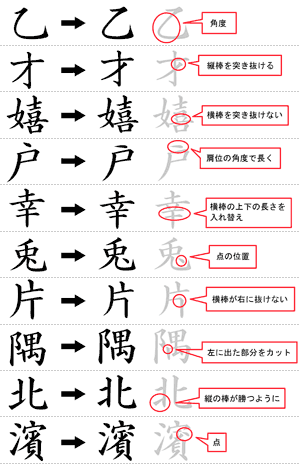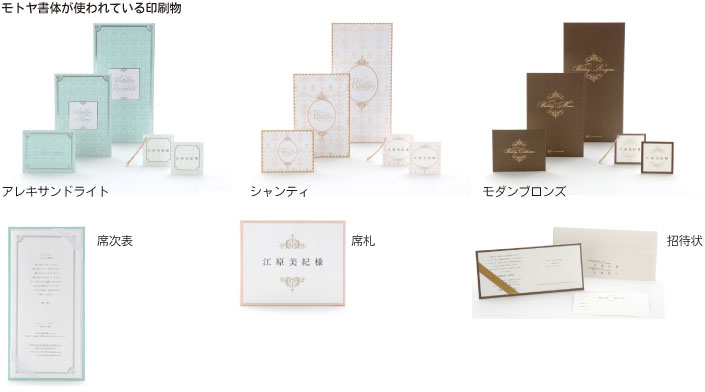
モトヤフォントの導入事例 お客様の声
『株式会社マイプリント』
昭和41年に設立された株式会社マイプリントは、創業当時から招待状や席次表、席札といった婚礼印刷物や年賀状印刷を手掛けてきた企業です。婚礼印刷物は全国 1,500以上のホテルや式場と直接取引し、年賀状でも代理店契約を結ぶ店舗が 14, 000以上。パーソナル印刷分野では国内シェアトップの実績を誇ります。
<右写真>新たに導入されたモトヤフォントによってデザインされたもの。こうした婚礼印刷物は書体デザインに求められる独自ルールが多く、これまで対応に苦慮されてきたそうです。
マイプリントが〝さらなるサービス力の強化〟を目指して導入されたのがモトヤフォントです。とくに「婚礼印刷物で必要とされる〝書体デザイン〟が新フォント導入の原動力」と語る同社生産本部の田中元氏さんに、導入の経緯について伺いました。
「婚礼印刷物は、これまでの様に格式を重んじた和風のフォーマルな物から洋風なデザインも多く選ばれるようになり、多様化して来ています。」と語る田中元氏さん。婚礼印刷物に使われる文字もデザインバリエーションの増加に合わせ柔軟に使い分けることが求められる時代になりました。
一方で婚礼印刷物に使われる書体には慶事使用ならではの慣習やルールがあります。たとえば「草」という文字。楷書体では草冠の間が離れている書体もあり、これは婚礼印刷物では避けておきたい文字のデザインということになります。また、席次表や席札、あるいは招待状と婚礼印刷物の多くにお名前が印刷されますが、これらは同じ書体が使われるとは限りません。印刷物の種類によって書体を使い分けた際、文字の形状が違っていないようにチェックすることもマイプリントの大切な仕事です。
「文字の形状やデザインへの要望に長年対応していく中で、書体を串刺しにチェックして違う文字があればそれを吸収した外字を作る、あるいはその都度文字を修正するなどノウハウが蓄積されてきました。
手作業による文字修正は確実ですが、手間と時間が掛かります。特に最近では短納期への要望が高く、『製販刷新プロジェクト』を起ち上げて、生産工程全体を見直すことになりました。
このプロジェクトの一つとして挙げられたのが『組版エンジンの刷新』です。組版エンジンにはフォント環境が重大な影響を及ぼすため、“作成した文字を外字として管理し、自動化された印刷ワークフローを構築する”ことを目標にフォントベンダー選びが始まりました。
製販刷新プロジェクト内で作成された文字形状のチェックリスト。婚礼印刷物ならではの考え方で細部に渡る文字の修正を行っています。このリストはモトヤにも渡され、書体導入時の変更事案としても用いられました。
新システム導入が構想されたのは 2009年のこと。ここでフォントベンダー選びをするにあたって、マイプリントは以下の 3つのポイントを掲げました。
①「文字品質の高さ」
これは婚礼印刷物というフォーマルな印刷物を作る上での絶対的な条件です。
②「違和感のない書体」
既存のお客様から見て変更前後で違和感がないように、さらなる信頼が得られるように。
③「信頼できるフォントベンダーであること」 技術の裏付けがあった上で多岐にわたる要望を安心して任せられること。
これらの要点から選ばれたのがモトヤです。フォントベンダーの比較時にはさらに 3つの視点があり、選択時にはかなり細かい部分にまでアンテナを張った検討が重ねられました。
「まずは見た印象から得られる〝視覚的〟な要素、そして印刷分野ごとに少しずつ異なるフォントベンダーの市場シェアを調べ、私たちの要求に自動組版システムで組み込める高い技術力を持っているフォントベンダーとして挙がったのがモトヤさんの書体でした。とくにオリジナル筆文字フォントのOTF化、ライセンス契約、和文はもちろん欧文もサポートしてくれること、すでに自作している外字を活かせるかどうかなど、私たちの要求はかなり厳しいものだったと思いますが、モトヤさんはすべてのリクエストに応えてくれました。今思えば、〝フォントの形を変えて欲しい〟なんて良く言いましたよね。私たちのニーズを的確に汲んで速いレスポンスで対応してもらえたので、(プロジェクトの実施項目の中でも)書体に関しては一番スムーズに進んだと思います」(田中元氏さん)
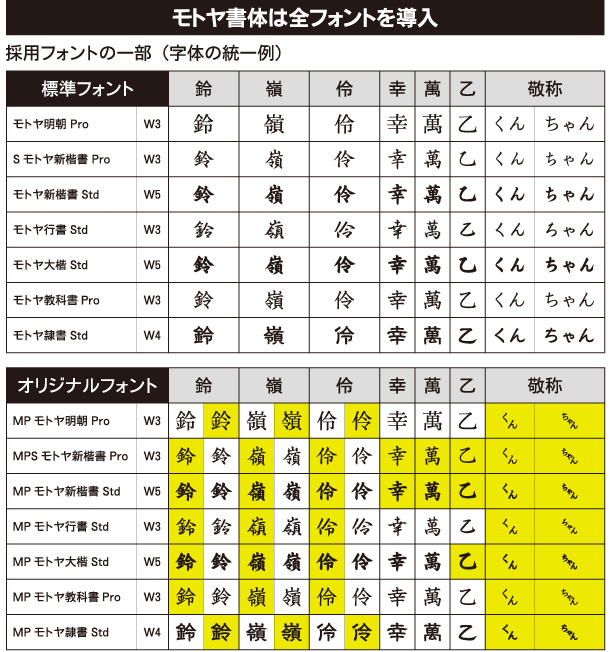
黄色部分は市販と異なるカスタマイズフォントです。
「婚礼印刷物ではお名前を扱うことが多く、外字の作成はかかせません。以前はオペレータが個人単位で作っていたので書体毎の文字形状管理が大変だったのですが、今回は一度作成した文字をすぐに再利用できるようなシステムになり、さらに異体字切り替えできるようになりました。また、OpenTypeフォントによってJISコードの制限からも解放されたので、現場スタッフからも高評価を得ています」。
マイプリントが何よりも大切にしているのが“お客様に最高のサービスをご提供すること”。一生に一度の晴れの舞台で印刷物を通じてお手伝いするという強い思いがあります。フォントは単純にテキストデータとしてではなく、デザインやサービスの一部としても重要な役割を果たします。とくに婚礼印刷物のほとんどはパーソナル印刷なので、文字の品質と形状には並々ならぬこだわりを持って取り組まれているそうです。モトヤが選ばれたのも、書体カスタマイズに対する技術力が認められてのことでした。田中氏は「もちろん、商用二次使用も含め将来のビジネス展開も重視しましたよ。結果として、モトヤに決めて大正解でした」と話します。
“お客様の要望を先取りして文字の形状をデザインする”─マイプリントが求めるカスタマイズ書体への探求からは、新しい書体の使い方のヒントが見えてくるのではないでしょうか。
導入された書体には「モトヤ隷書体」もあります。これは全国チェーン展開する式場からのリクエストによるものだそうです。
明朝体の横棒もかすれずに印刷できる点も、「文字デザインがしっかりしている証拠」と高く評価して頂きました。